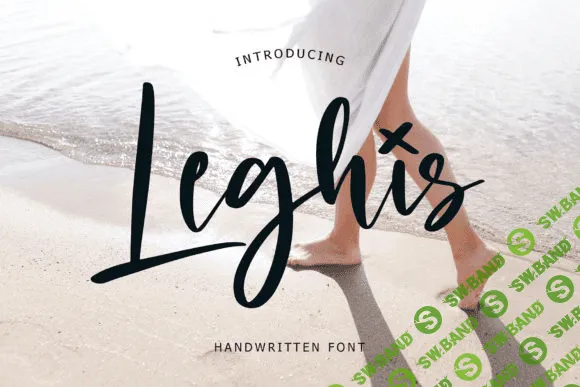
Leghis - это причудливый шрифт со спокойной темой, отличающийся прекрасным стилем.
Независимо от темы, этот шрифт будет невероятно полезным для библиотеки ваших шрифтов, так как он способен возвысить любое творение.